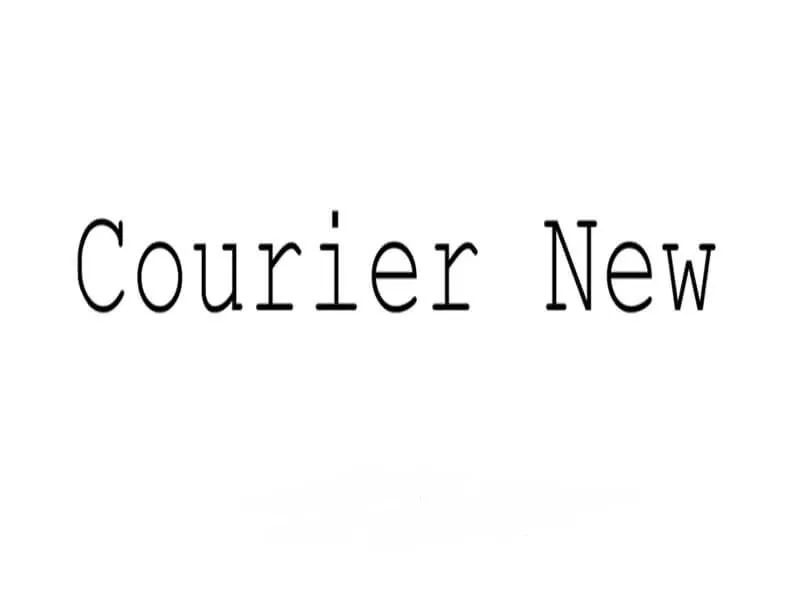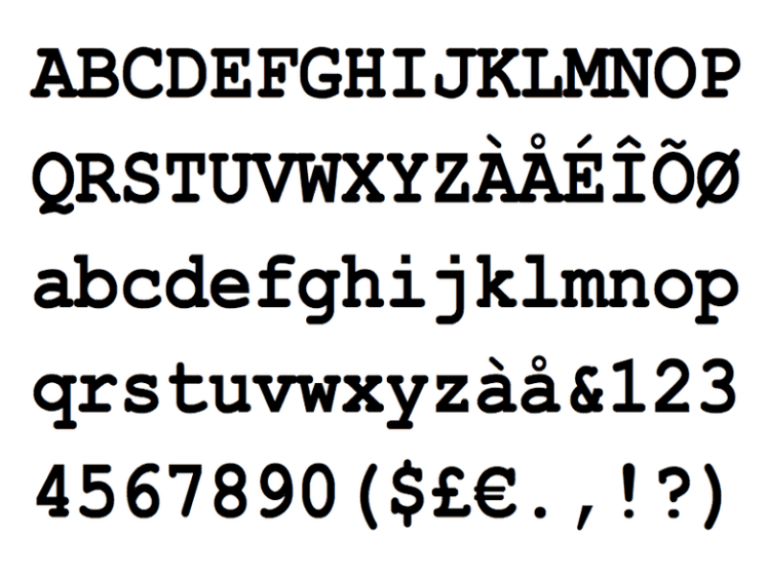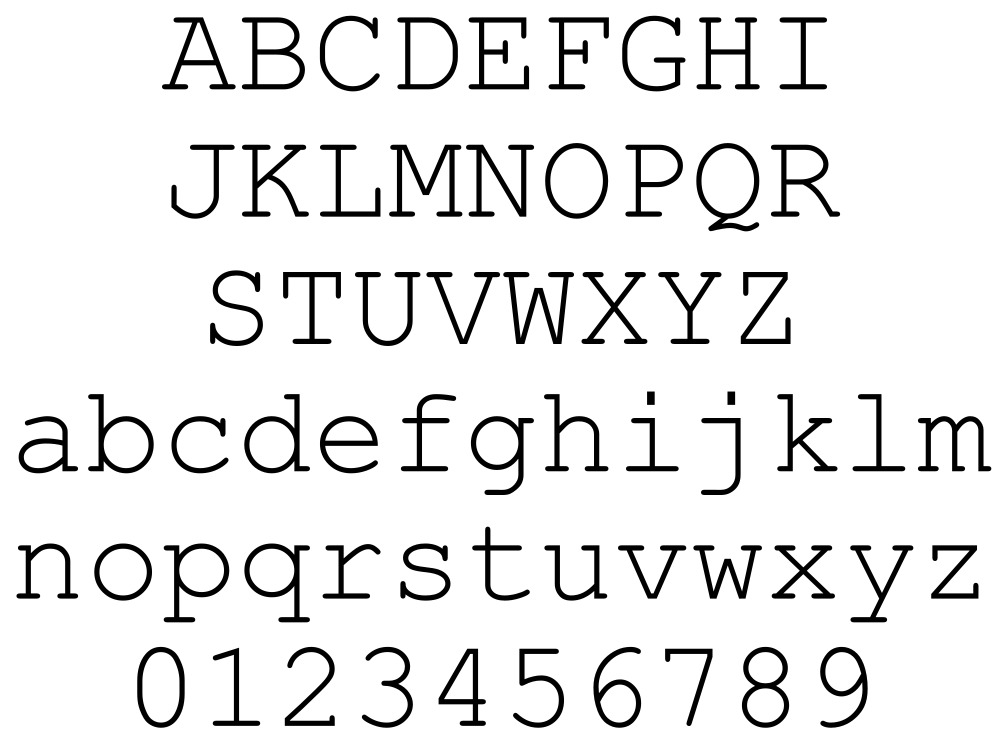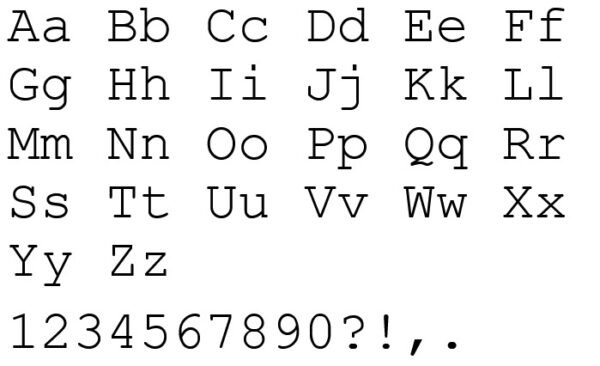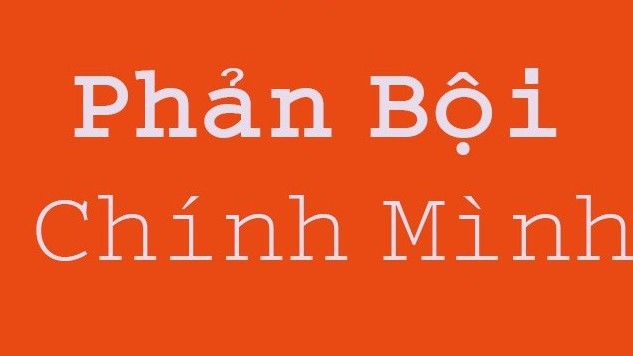
Font Courier New Việt hóa là bộ phông chữ thuộc dòng Monospaced Slab Serifh huyền thoại, mô phỏng sinh động các nét gõ đập mực của máy đánh chữ cơ khí IBM thế kỷ 20. Với đặc tính mỗi con chữ đều chiếm một diện tích bề ngang chuẩn xác như nhau trên dòng kẻ, phông chữ Courier New là chất liệu trực quan tuyệt vời để các kiến trúc sư, kỹ sư kết cấu trình bày các bảng thống kê vật tư dầm thép, danh mục thiết bị điện nước hay các bản vẽ mã nguồn tự động hóa nhà lắp ghép.
Cấu trúc độ rộng cố định và khí chất cơ khí của font Courier New Việt hóa
Điểm cuốn hút của font Courier New Việt hóa nằm ở tính kỷ luật tuyệt đối về mặt không gian: từ chữ cái hẹp như ‘i’, ‘l’ đến các chữ cái rộng như ‘w’, ‘m’ đều đứng trong một khung hình chữ nhật có kích thước đồng nhất. Cấu trúc chân chữ vuông vức kết hợp cùng các góc bo cơ học mang lại cảm giác chân thực như những trang tài liệu mật hay biên bản điều tra hiện trường thời kỳ tiền kỹ thuật số.
Sự ổn định về mặt thị giác của dòng font này tạo nên cảm giác minh bạch, mộc mạc và chuẩn xác về mặt số liệu. Khi kết hợp cùng các bề mặt vật liệu kiến trúc công nghiệp như vách tôn sóng container, tấm thép đục lỗ, mặt bàn kim loại xước mờ hay bảng mạch điện tử trong các căn nhà thông minh, Courier New tạo nên sự tương thích thẩm mỹ đầy cá tính.
| Phân loại phong cách | Monospaced / Slab Serif / Typewriter Style |
| Mục đích phù hợp | Bảng thống kê vật liệu, sơ đồ kết cấu, kịch bản |
Tư vấn từ chuyên viên: Courier New sở hữu khoảng cách chữ rộng tự nhiên do đặc tính đơn khoảng. Để bản thiết kế đạt hiệu quả thẩm mỹ tốt, bạn nên sử dụng phông chữ này cho các bảng số liệu kỹ thuật, danh mục chi tiết cấu kiện hoặc mã hiệu công trình.
03 Ứng dụng phông chữ Courier New vào công tác xây dựng
Nhờ cấu trúc căn lề hoàn hảo và tính gợi hình cơ khí mạnh mẽ, bộ phông chữ này mang lại giá trị thực tế lớn trong khâu lập hồ sơ và thi công công trình hiện đại:
- Bảng thống kê vật tư và Quy cách thép trên Bản vẽ CAD: Độ rộng cố định của Courier New giúp các cột số liệu về chiều dài thanh thép, diện tích tấm panel hay tải trọng bu lông luôn thẳng tắp theo trục dọc, hạn chế tối đa nhầm lẫn cho đội ngũ bóc tách khối lượng.
- Sơn mã số nhận diện trên vách Thùng Container: Những con số mang phong cách máy đánh chữ khi sơn stencil lên bề mặt kim loại sóng tôn sẽ giúp các căn văn phòng container toát lên vẻ thô ráp, bụi bặm đúng chất công nghiệp logistics.
- Trang trí tranh tường và Bìa hồ sơ giải pháp công nghệ: Sử dụng Courier New font Việt hóa để in các đoạn mã điều khiển tự động hóa hoặc trích dẫn tiêu chuẩn xây dựng giúp không gian làm việc toát lên phong thái khoa học và tính logic cao.
03 Lưu ý bố cục Courier New font Việt hóa thẳng hàng và ngăn nắp
Để khai thác hiệu quả vẻ đẹp của dòng font máy đánh chữ này mà không làm tốn diện tích trang in, người thiết kế nên lưu tâm một số kinh nghiệm sau:
- Tận dụng tính năng căn cột tự nhiên: Nhờ các con chữ có độ rộng bằng nhau, bạn có thể dễ dàng căn chỉnh các bảng biểu kỹ thuật phức tạp chỉ bằng phím Space hoặc phím Tab mà không cần kẻ quá nhiều khung viền rườm rà.
- Kiểm soát kích thước hiển thị: Courier New chiếm diện tích bề ngang khá lớn so với các phông chữ tỷ lệ (Proportional fonts). Bạn nên giảm nhẹ kích thước chữ xuống khoảng 9-11pt trong các tài liệu nhiều chữ để trang in không bị dàn trải quá mức.
- Lựa chọn gam màu đơn sắc dứt khoát: Phông chữ phát huy hiệu quả thị giác cao khi phối cùng màu đen mực in trên nền giấy ngả vàng cổ điển, hoặc chữ xanh lá dạ quang / trắng tinh trên nền màn hình đen, mô phỏng các dòng lệnh máy tính xưa.